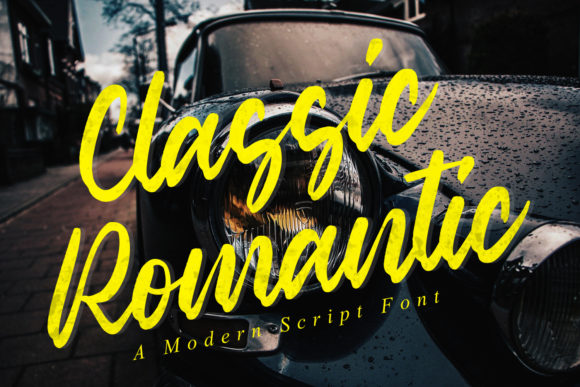
Classic Romantic
Die richtigen Designelemente zu finden, kann eine Herausforderung sein, aber Classic Romantic bietet eine außergewöhnliche Sammlung, die Ihre Arbeit sofort aufwertet.
Egal, ob Sie POD-Produkte (Print on Demand), Hochzeitseinladungen oder Social-Media-Grafiken erstellen, Classic Romantic ist die ideale Wahl.